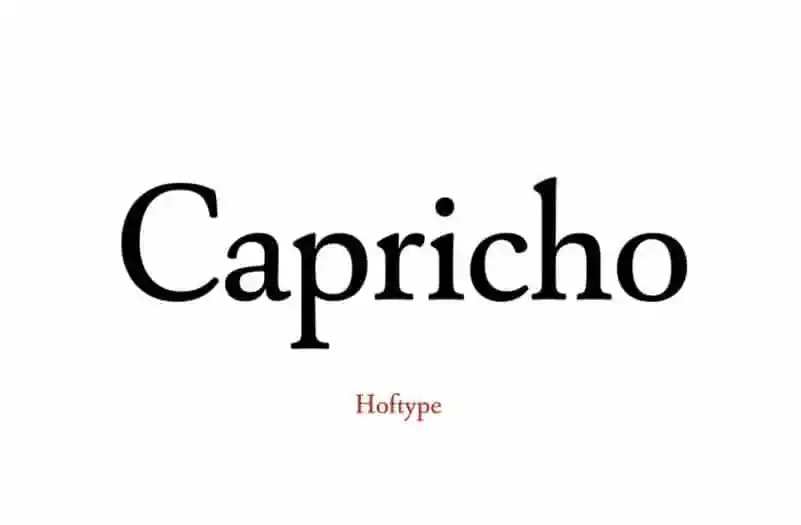
A fonte Capricho Serif é uma tipografia serifada criada pela Hoftype, repleta de detalhes suaves que dão a impressão de um design elegante e sofisticado. Suas formas leves e fluidas permitem criar textos impecáveis, especialmente em ambientes profissionais ou editoriais mais formais. Esse tipo de fonte se destaca por unir elementos clássicos de uma serifada do século XVII com um toque único que a torna inconfundível e autêntica. Seja para assinaturas elegantes em sites corporativos, gráficos publicitários ou até mesmo documentos formais, Capricho Serif é um excelente recurso para quem busca uma fonte serifada que combine elegância com personalidade. A Hoftype certamente não caiu na mesmice ao desenvolver essa fonte, e em vez disso trouxe consigo um toque diferenciado que faz dela uma opção irresistível para qualquer designer gráfico.